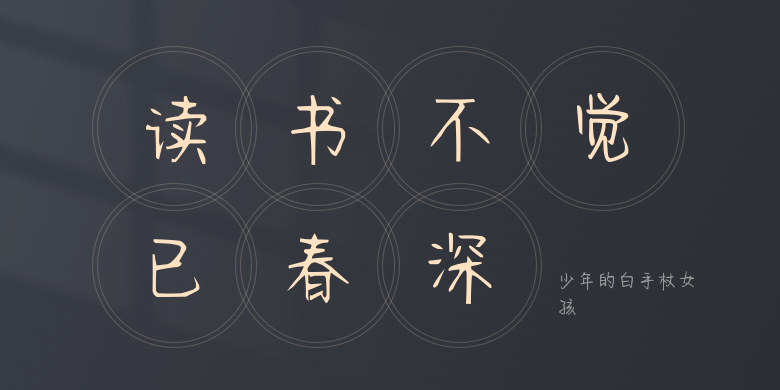
少年的白手杖女孩
少年的白手杖女孩,这款字体结构工整、笔画清晰,兼顾美观与易读性,适用于标题、正文、海报、包装、LOGO 等多种场景。字形优雅稳定,风格百搭耐看,适配日常排版与创意设计,让文字呈现更舒适、更具质感。少年的白手杖女孩一笔一画,皆是细节,以均衡的比例、流畅的线条打造舒适视觉体验,字形端正大气,风格简约现代。无论是商业设计、品牌宣传还是日常排版,都能轻松驾驭,让文字更有格调与力量。少年的白手杖女孩字体下载。